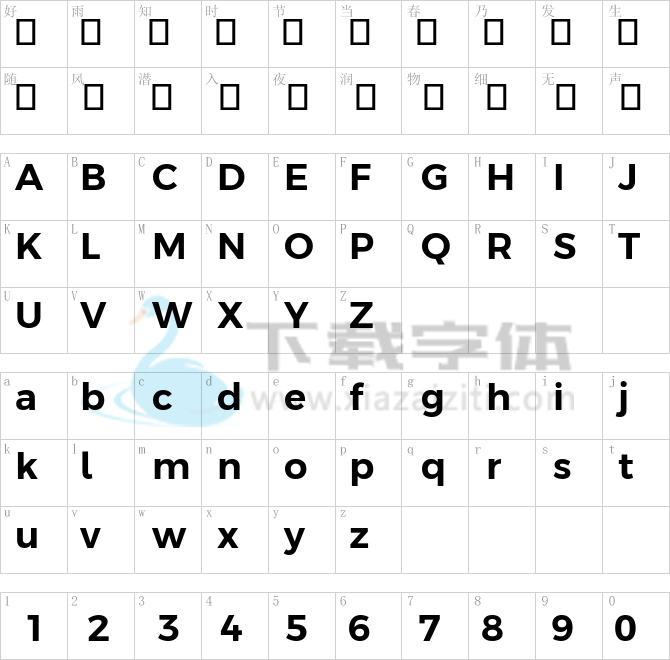
Argentum Sans SemiBold.ttf字体下载,这款字体结构工整、笔画清晰,兼顾美观与易读性,适用于标题、正文、海报、包装、LOGO 等多种场景。字形优雅稳定,风格百搭耐看,适配日常排版与创意设计,让文字呈现更舒适、更具质感。Argentum Sans SemiBold.ttf字体下载一笔一画,皆是细节,以均衡的比例、流畅的线条打造舒适视觉体验,字形端正大气,风格简约现代。无论是商业设计、品牌宣传还是日常排版,都能轻松驾驭,让文字更有格调与力量。Argentum Sans SemiBold.ttf字体下载字体下载。